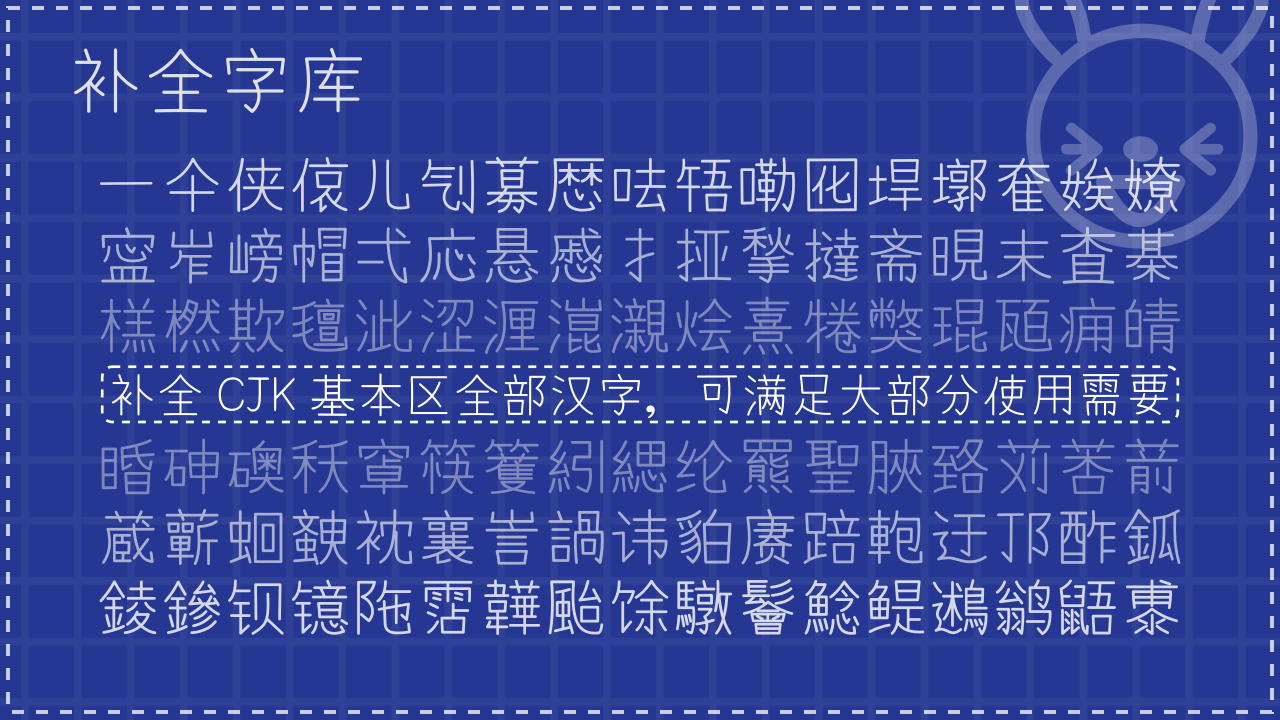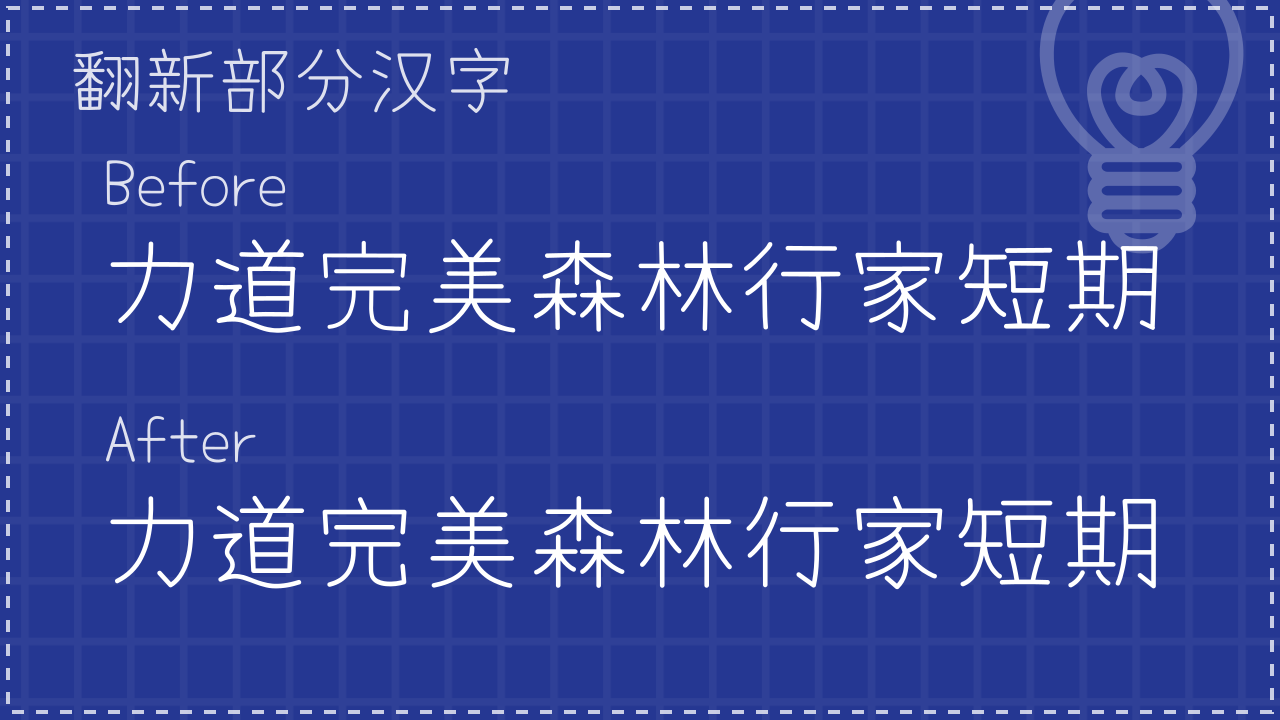
有梦体
别称:有夢體 / Yomeng Script
有梦体 / 有夢體 / Yomeng Script
本字体由 Yomogi 字体二次开发而成。
- 补全字库 补全 CJK 基本区内全部汉字,可满足大部分使用需要。
- 字形本土化 将大部分汉字调整为更符合陆标的字形,少部分汉字或部件为维持原有风格,保留原有字形或采用折中写法。
- 翻新部分汉字 翻新原字体当中部分风格差异较大的汉字,加强风格一致性。
- 修复问题字形 修复原字体中一些笔画或码位存在问题的汉字。